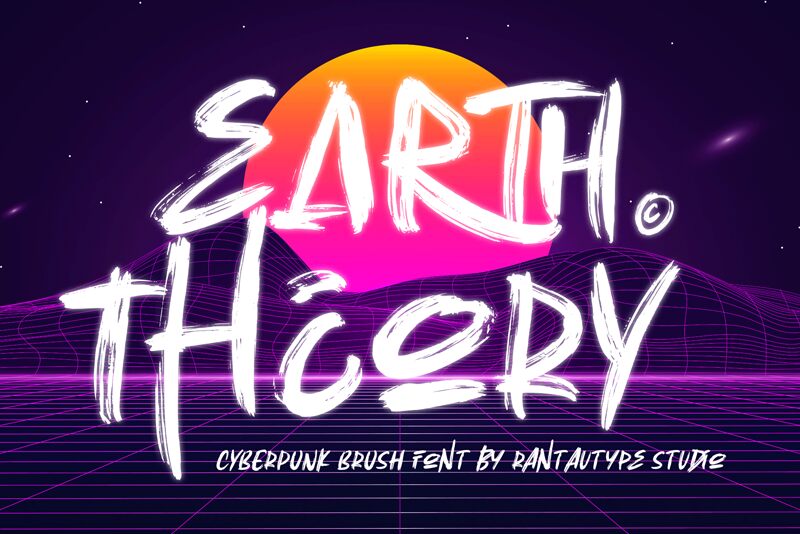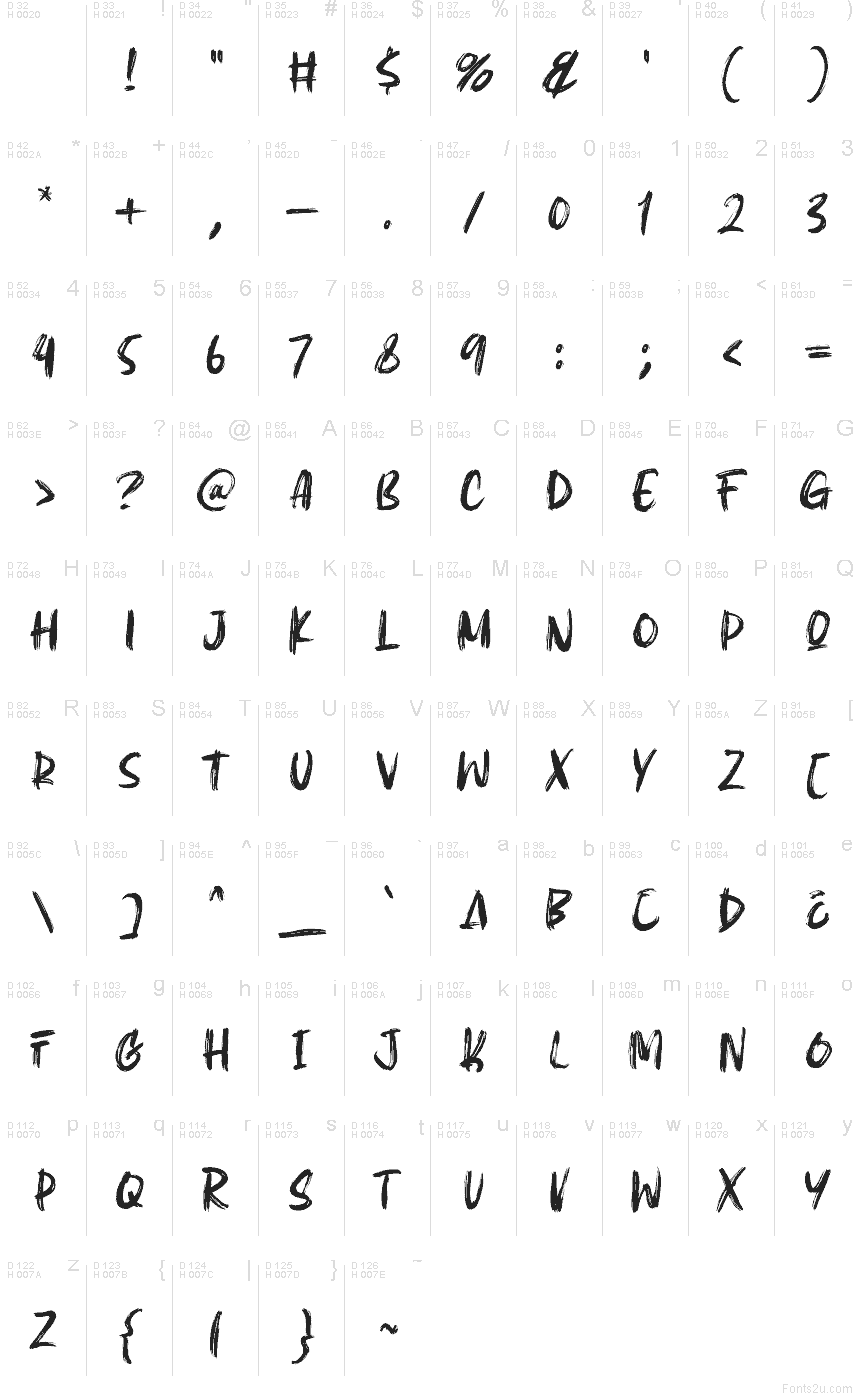
Earth Theory
Earth Theory от Rantautype Studio — это бесплатный акцидентный шрифт в стиле сухой кисти (dry-brush) с грубой, «ручной» эстетикой. Буквы выглядят набросанными на ходу, с неровными краями, резкими штрихами и высокими, неравномерными формами, что придает им дерзкую, плакатную энергию — в противовес вылизанным скриптовым шрифтам.
Он идеально подходит для музыкальных флаеров, streetwear-графики, приключенческого брендинга, книжных обложек и заголовков, где текстура кисти должна задавать тон. Как бесплатный шрифт, он также хорош для коротких заголовков, надписей на упаковках и броских постов в соцсетях, особенно если вы хотите, чтобы заглавные буквы выглядели «живыми», как будто их выцарапали, и слегка потрепанными.